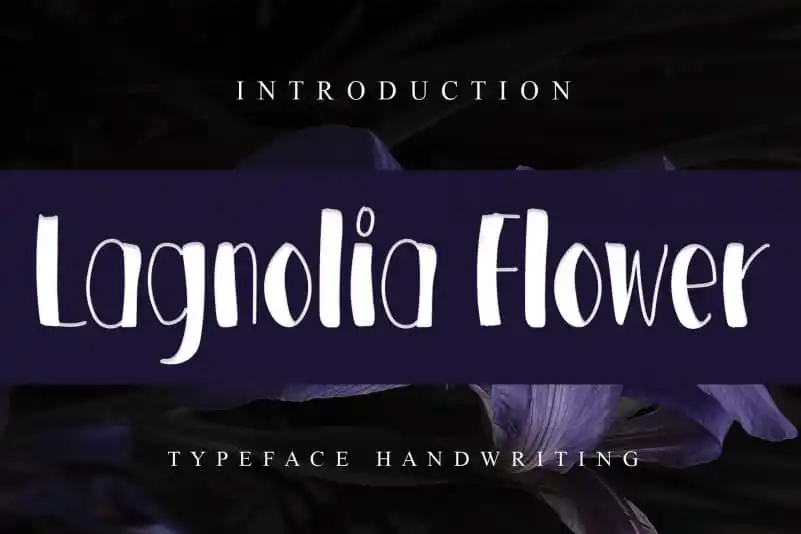
Lagnolia Flower Display Font – Fonte Grátis
Lagnolia Flower Display Font
A Lagnolia Flower Display Font é uma elegante fónt que encanta por sua simplicidade e propriedade limpa. Ideal para designers que buscam uma fonte fresca e moderna, essa escolha criativa torna seus trabalhos de design viverem mais intensamente. Perfeita para aplicar em materiais visuais como cartazes, flyers ou designs gráficos envolventes, a Lagnolia Flower Display Font convida os olhos ao criar um visual vibrante e atemporal. Esta fónt foi projetada por andikastudio e é certamente uma escolha inteligente para aqueles que procuram um elemento de elegância na sua próxima criação visual.